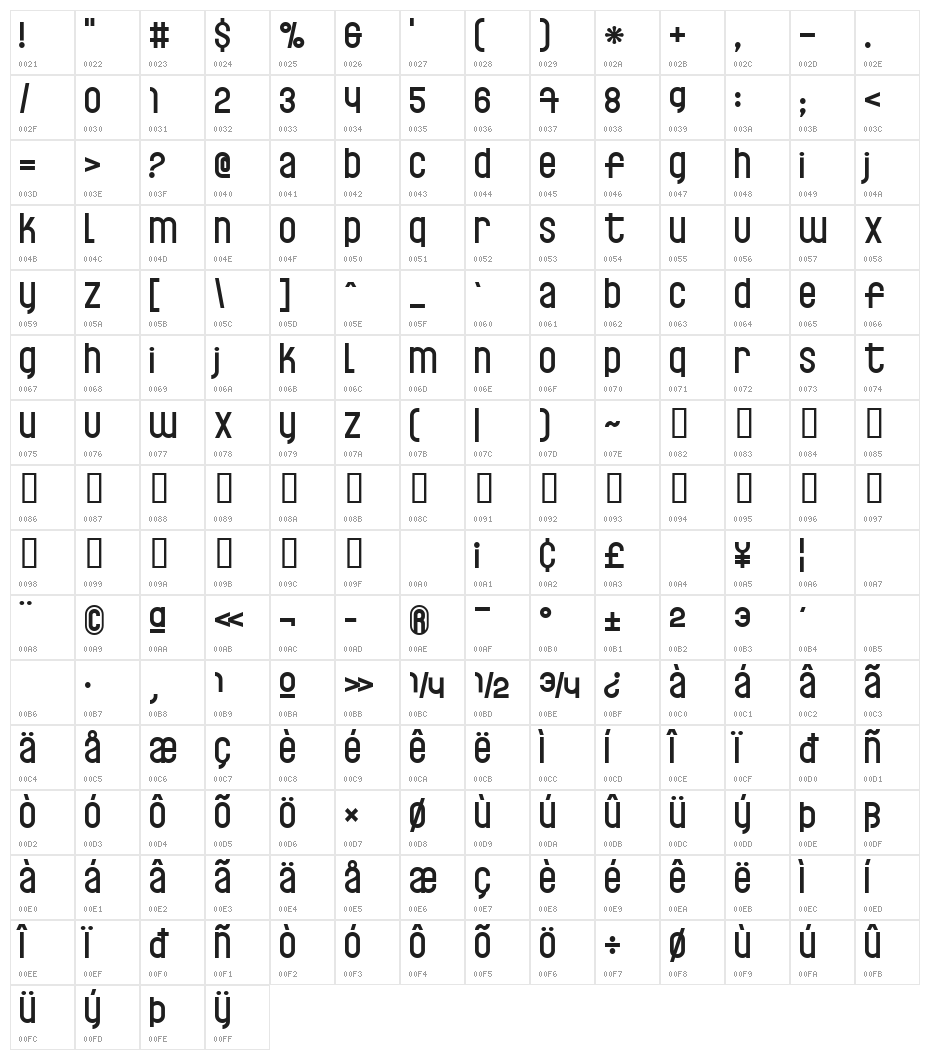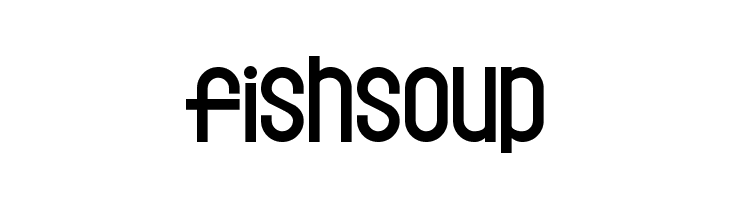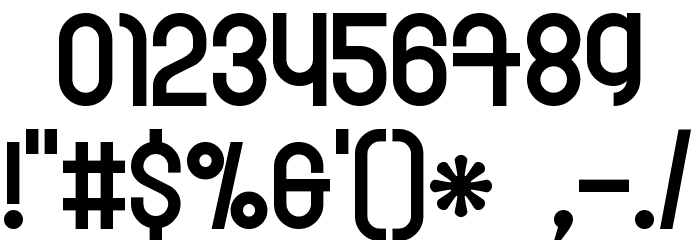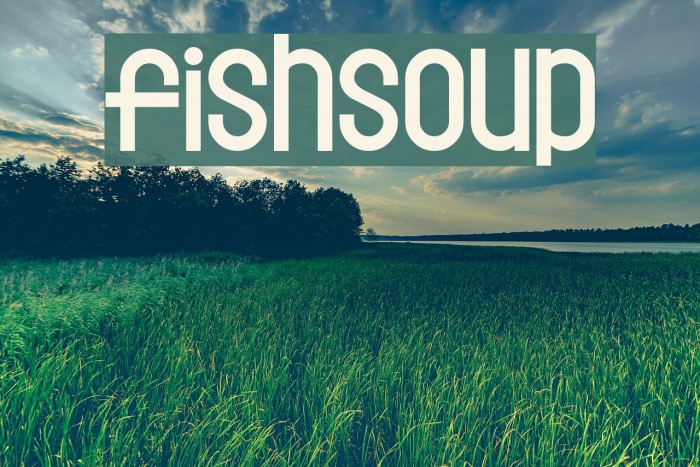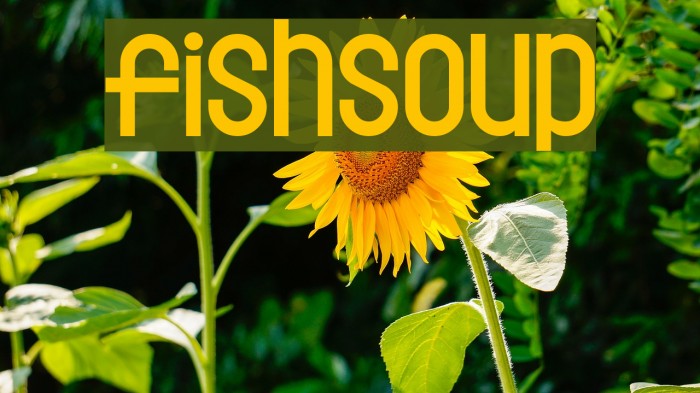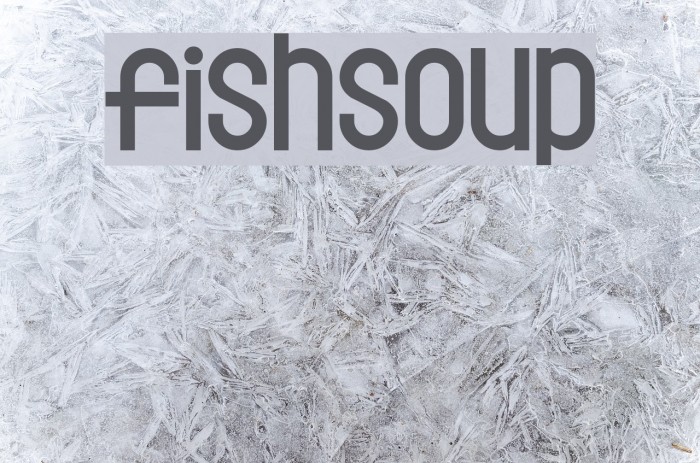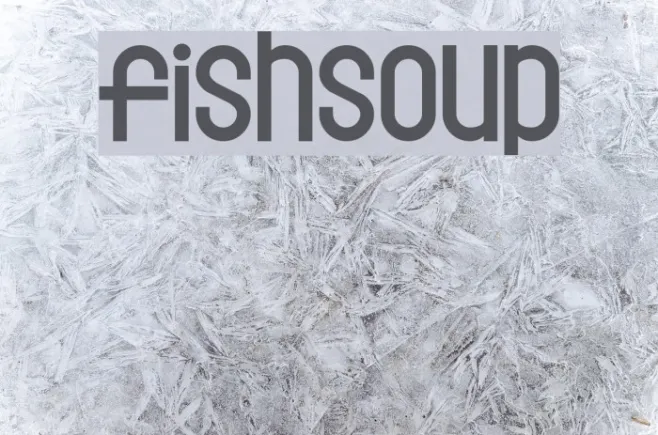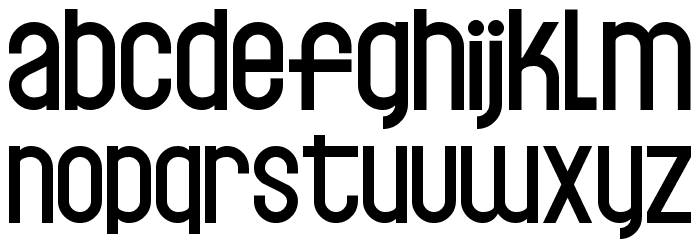
Fishsoup Font
| Categorie | Round |
| Caso d'uso | Headlines, Logos, Branding |
| Progetti proposti | Ideal for branding, advertising, packaging, and digital media projects where a modern and approachable look is desired. |